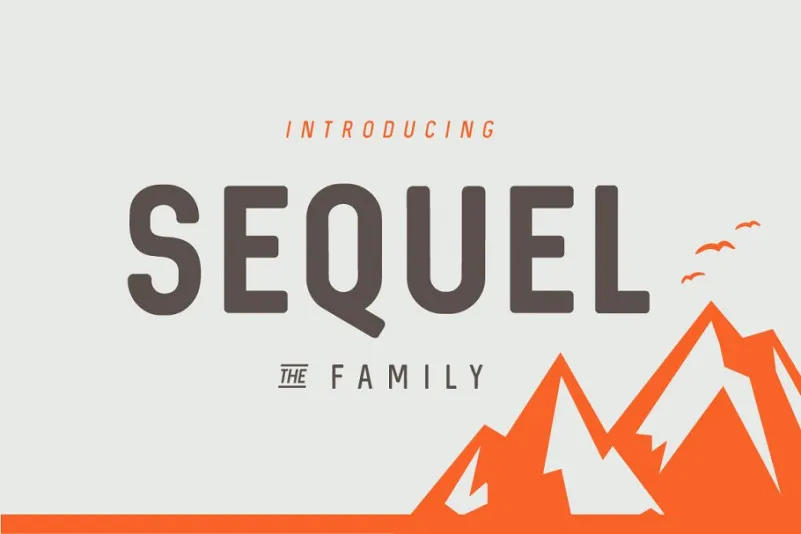
Sequel Font – Fonte Grátis
Sequel Font
A fonte Sequel é uma família de tipo sans serif que traz a característica de ser amigável e envolvente. Seu designer, Hamilton, criou algo único com as linhas contrastantes e terminais arredondados desta fonte, proporcionando um look elegante e sofisticado para aplicativos como logotipos, cartões de aniversário natalinos, convites de casamento, citações, anúncios e muito mais. A Sequel é perfeita para estilos que valorizam uma aparência moderna e fresca, mas ainda assim querem transmitir uma atmosfera acolhedora e confortável. Ideal para qualquer projeto gráfico em busca de um tipo sem serif que seja tanto atraente quanto versátil.